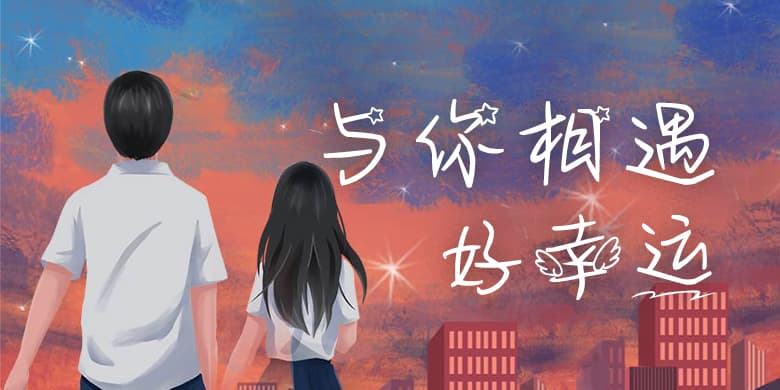
品牌:方正手迹设计师:刘晔发行时间:2019字库编码:大陆简体(GB2312-80)分类:创意书写字体属性:精品字
与你相遇好幸运是一款充满欢喜欢的字体,正如字体名称所传达的,幸运地相遇之后是心底温暖的欢喜。该字在结字上不拘法度,任由笔端自由流淌,使得该字气韵统却又不失其洒脱本性。再加上一些小挂件的点缀,使得该字更加趣味十足。适用于现代诗歌、短文的排版以及文化、商业类品牌的广告语设计。